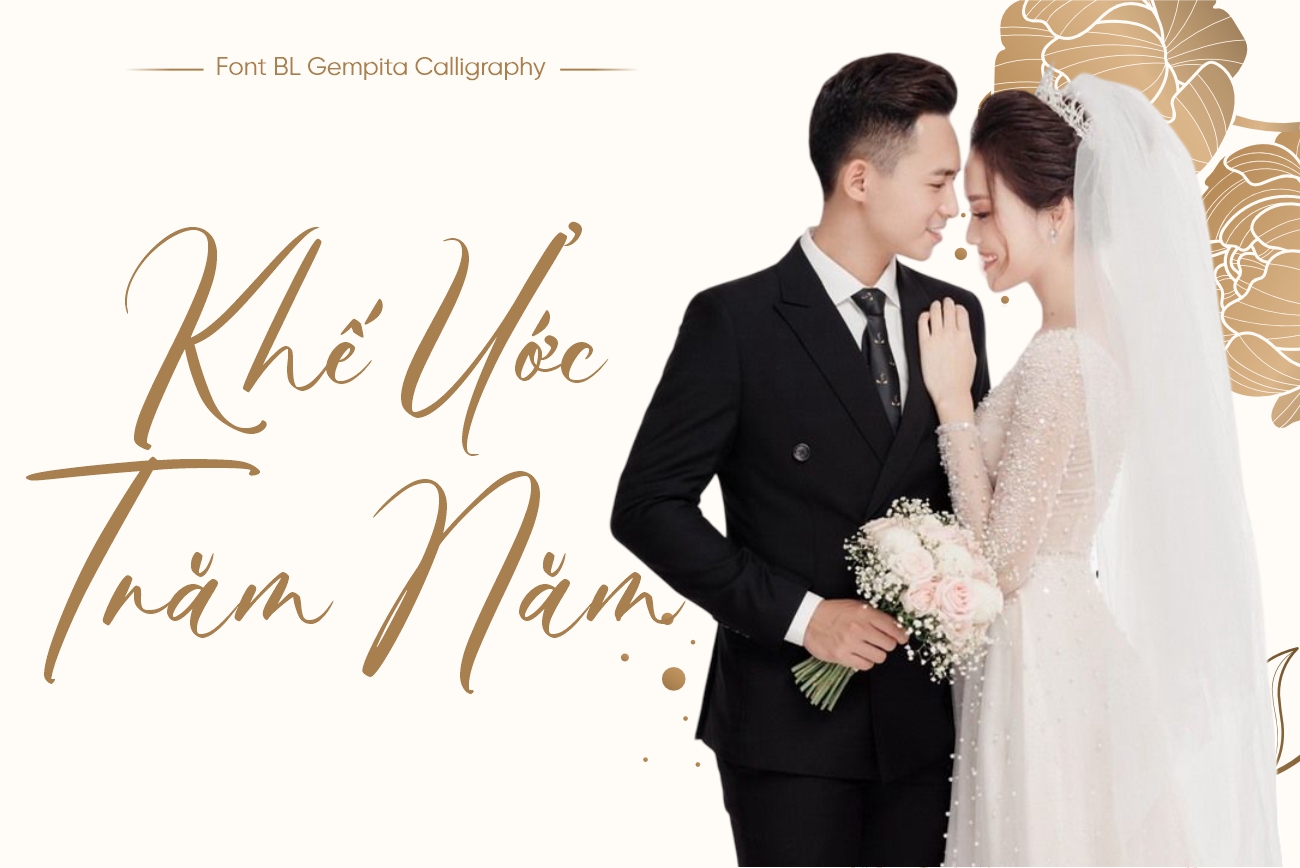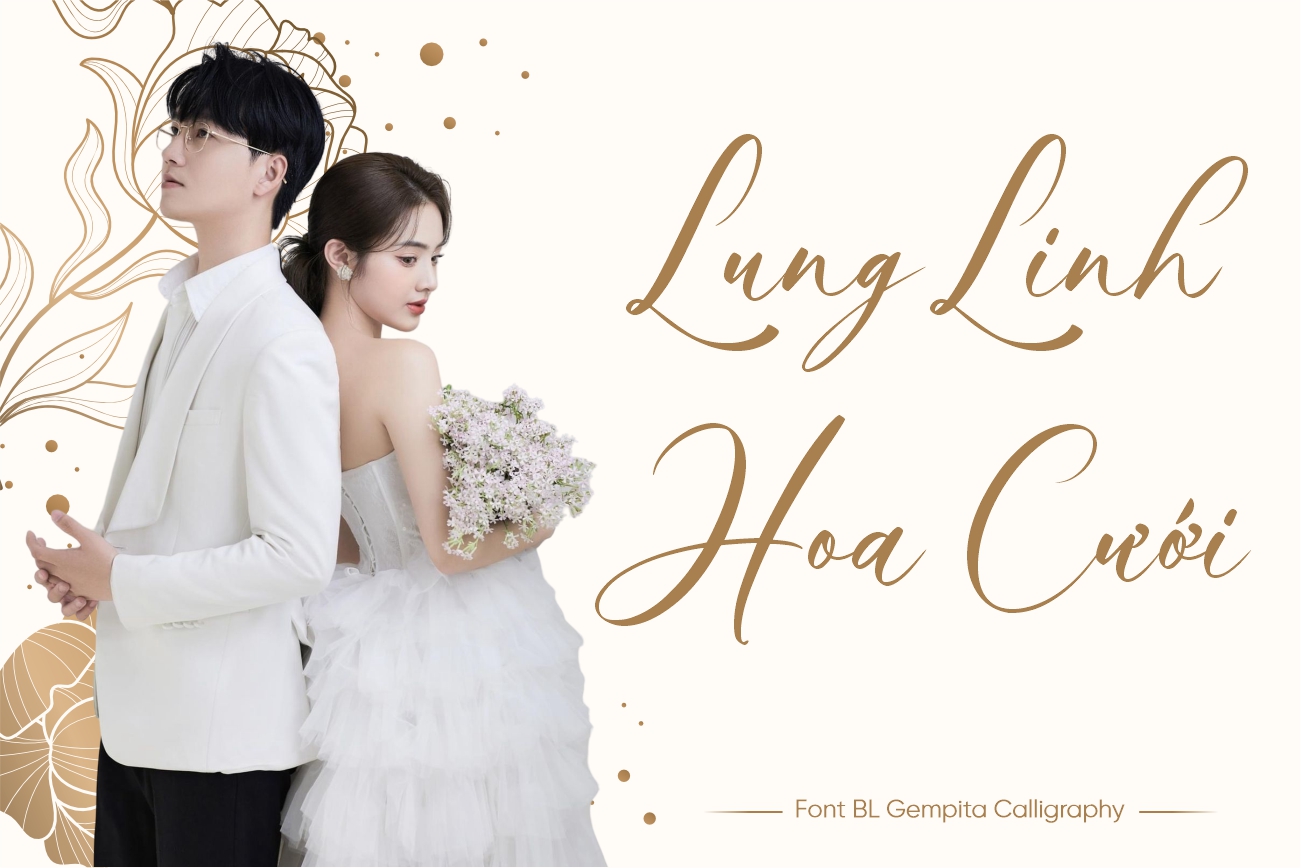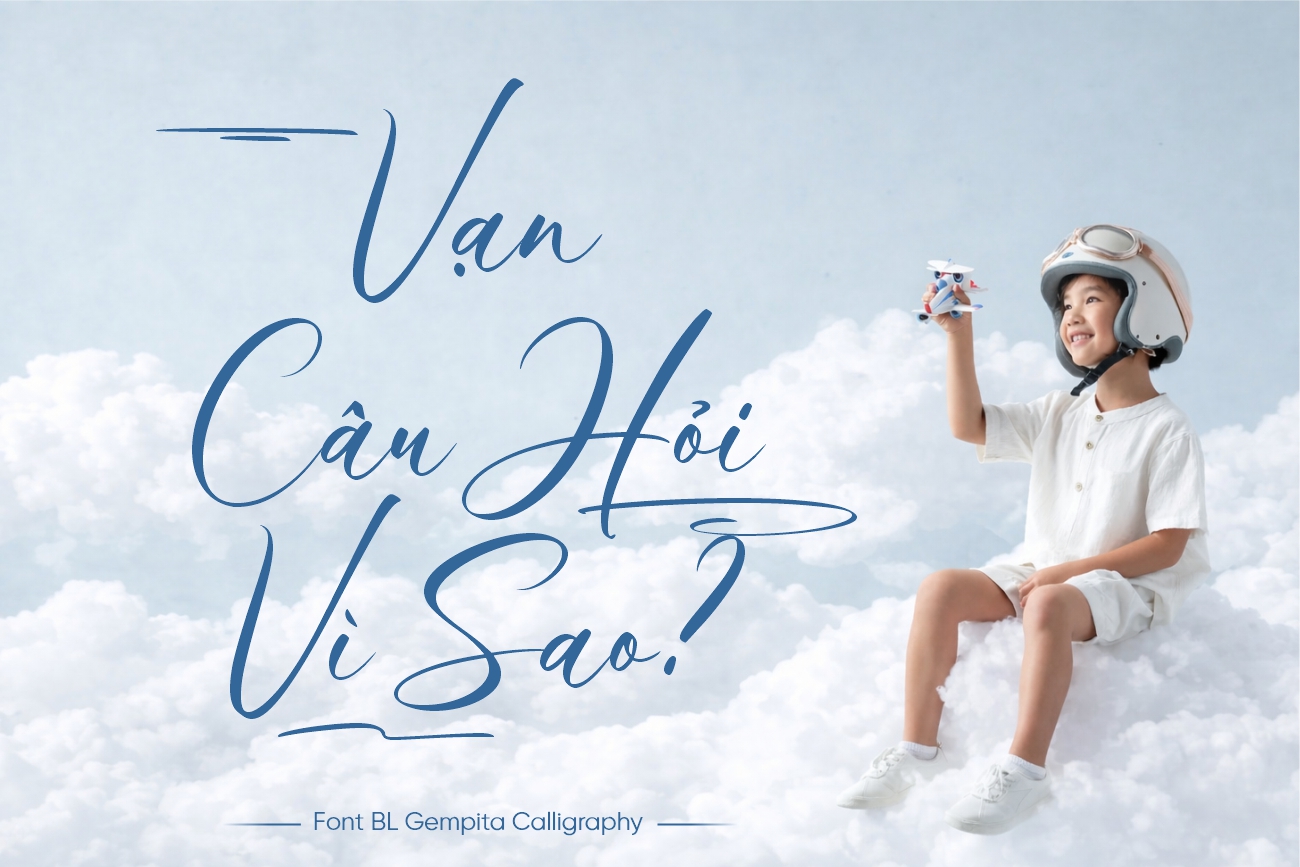
BL Gempita Calligraphy - Font brush quyến rũ, thanh lịch
BL Gempita Calligraphy là phiên bản Việt hóa của font chữ Gempita Calligraphy do Ainun Jinan thiết kế, được Team BL chỉnh sửa và hoàn thiện để đáp ứng nhu cầu sử dụng tiếng Việt một cách trọn vẹn. Font gốc mang đậm tinh thần thủ công của chữ viết tay nghệ thuật, lấy cảm hứng từ thư pháp truyền thống nhưng được thể hiện theo hơi thở hiện đại. Khi được Việt hóa, BL Gempita Calligraphy vẫn giữ nguyên cá tính ban đầu, đồng thời bổ sung đầy đủ dấu và ký tự tiếng Việt, giúp font vận hành mượt mà trong các ấn phẩm thiết kế mang tính cảm xúc và thẩm mỹ cao.
Về kiểu dáng, BL Gempita Calligraphy gây ấn tượng mạnh bởi những đường cong mềm mại và giàu nhịp điệu. Từng ký tự được tạo hình với đường nét uốn lượn tinh xảo, thể hiện rõ sự khéo léo và kiểm soát nét bút của người thiết kế. Các nét thanh – đậm chuyển đổi tự nhiên, không gắt, mang lại cảm giác nhẹ nhàng nhưng vẫn đủ nổi bật. Chính sự trau chuốt này giúp font toát lên vẻ phông chữ thư pháp quyến rũ, thanh lịch, phù hợp cho những thiết kế cần sự mềm mại, tinh tế và có chiều sâu nghệ thuật.
Một điểm đáng giá khác của BL Gempita Calligraphy nằm ở sự tỉ mỉ trong cấu trúc chữ. Các liên kết giữa ký tự được xử lý khéo léo, tạo dòng chữ liền mạch và uyển chuyển khi đặt trong bố cục dài. Nhờ các nét vẽ tỉ mỉ, font không chỉ đẹp khi dùng cho tiêu đề hay câu trích dẫn, mà còn phát huy hiệu quả trong thiệp mời, thiệp cưới, logo thủ công, bao bì cao cấp hoặc các ấn phẩm mang phong cách cá nhân hóa. Dù sử dụng trên nền đơn giản hay bố cục cầu kỳ, font vẫn giữ được sự cân đối và dễ đọc, không gây rối mắt.
Xét về nguồn gốc và ứng dụng, Gempita Calligraphy là minh chứng rõ nét cho phong cách thiết kế chú trọng cảm xúc của Ainun Jinan, nơi mỗi ký tự đều mang hơi thở nghệ thuật riêng. Qua quá trình Việt hóa, Team BL đã tối ưu lại tỷ lệ chữ và khoảng cách để phù hợp hơn với tiếng Việt, giúp font hoạt động ổn định trong nhiều định dạng thiết kế. Sự kết hợp giữa tinh thần thủ công và xử lý hiện đại tạo nên một phông chữ thư pháp quyến rũ, thanh lịch, dễ dàng chinh phục người dùng yêu thích cái đẹp mềm mại và tinh xảo. BL Gempita Calligraphy vì thế trở thành lựa chọn lý tưởng cho những ai đang tìm kiếm một font chữ giàu cảm xúc, có chiều sâu và giá trị thẩm mỹ bền vững.